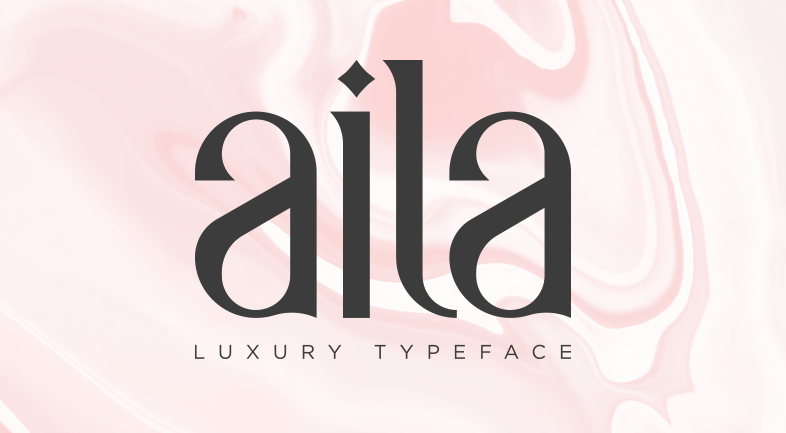
Introduzimos Aila Typeface! Desenvolvida e compartilhada por Shibu PG, Aila é uma tipografia moderna ideal para diversos tipos de aplicação. Esta tipografia se destaca como uma opção versátil que abrange uma ampla gama de tarefas gráficas, incluindo revistas, editoriais, posters, casamentos, websites, livros, identidade visual e branding, fotografia e moda. Seja para um projeto de marketing digital ou um site elegante, Aila oferece um visual limpo e moderno que não apenas complementa seu trabalho, mas o enriquece. Composta com simplicidade e elegância, a Aila é uma opção perfeita para aqueles que procuram estilização e clareza em cada letra.